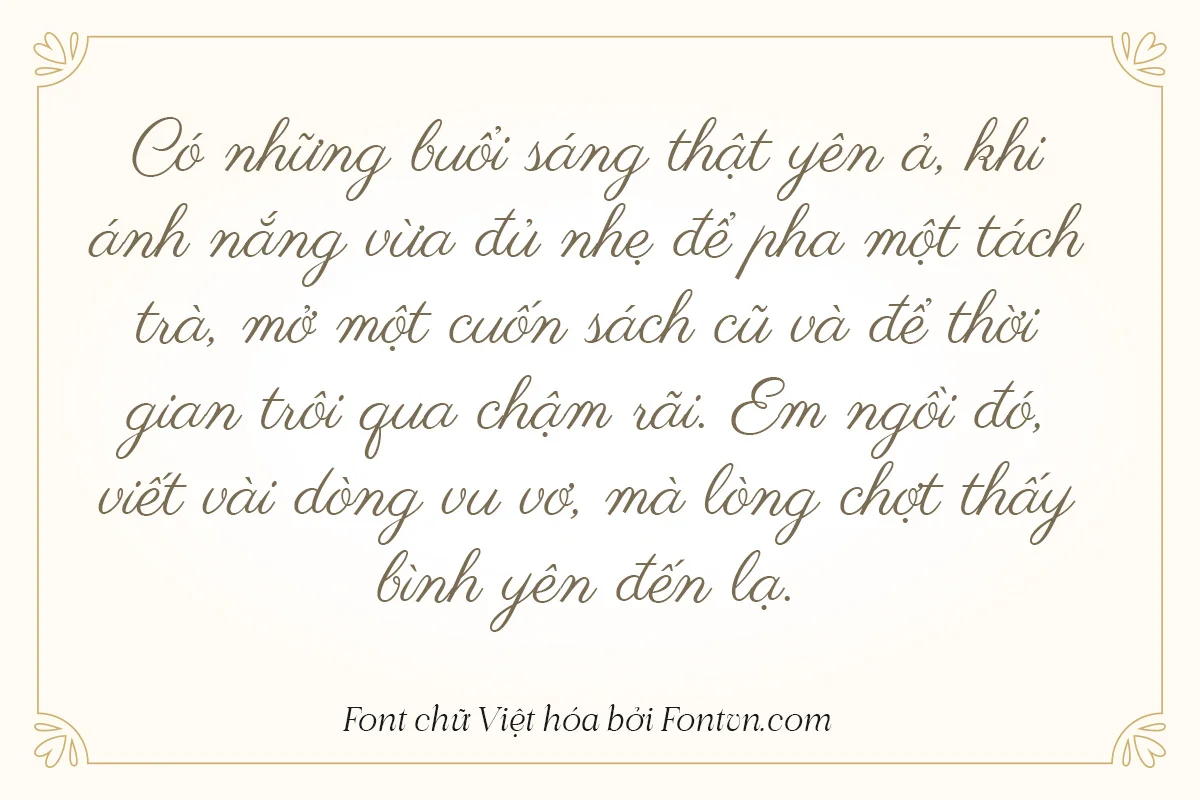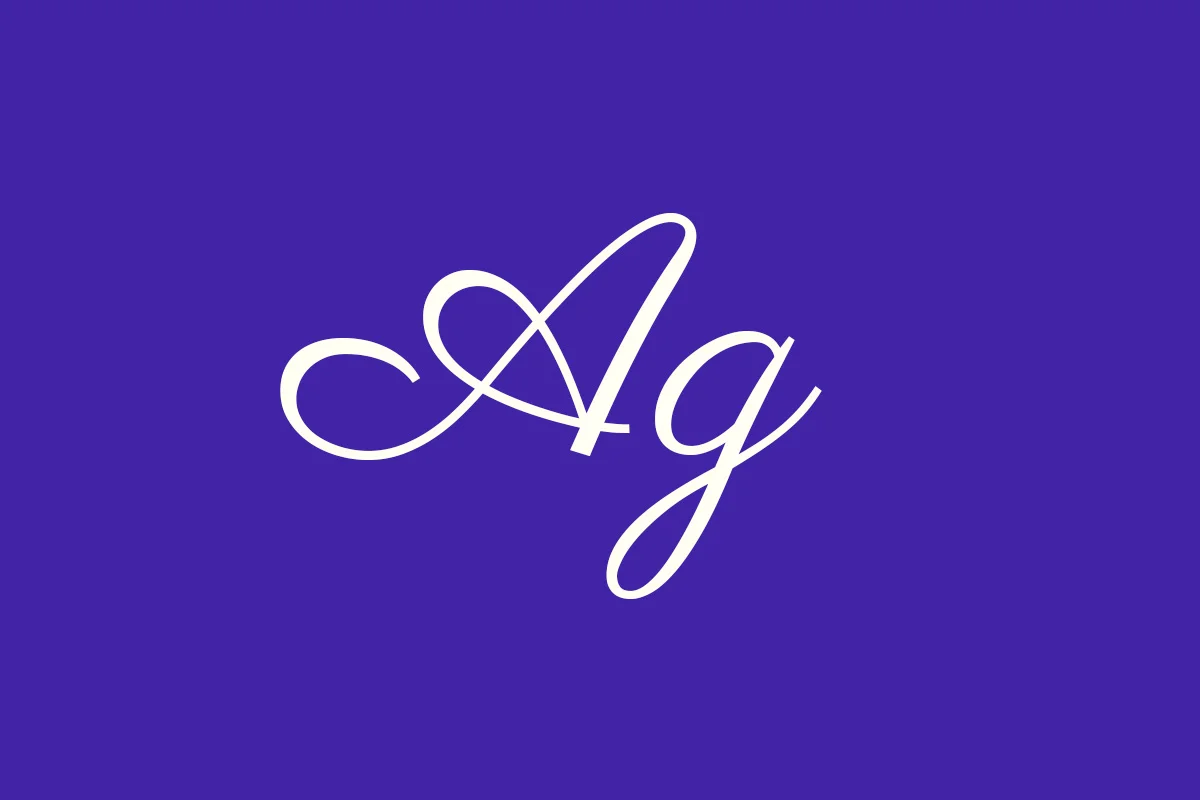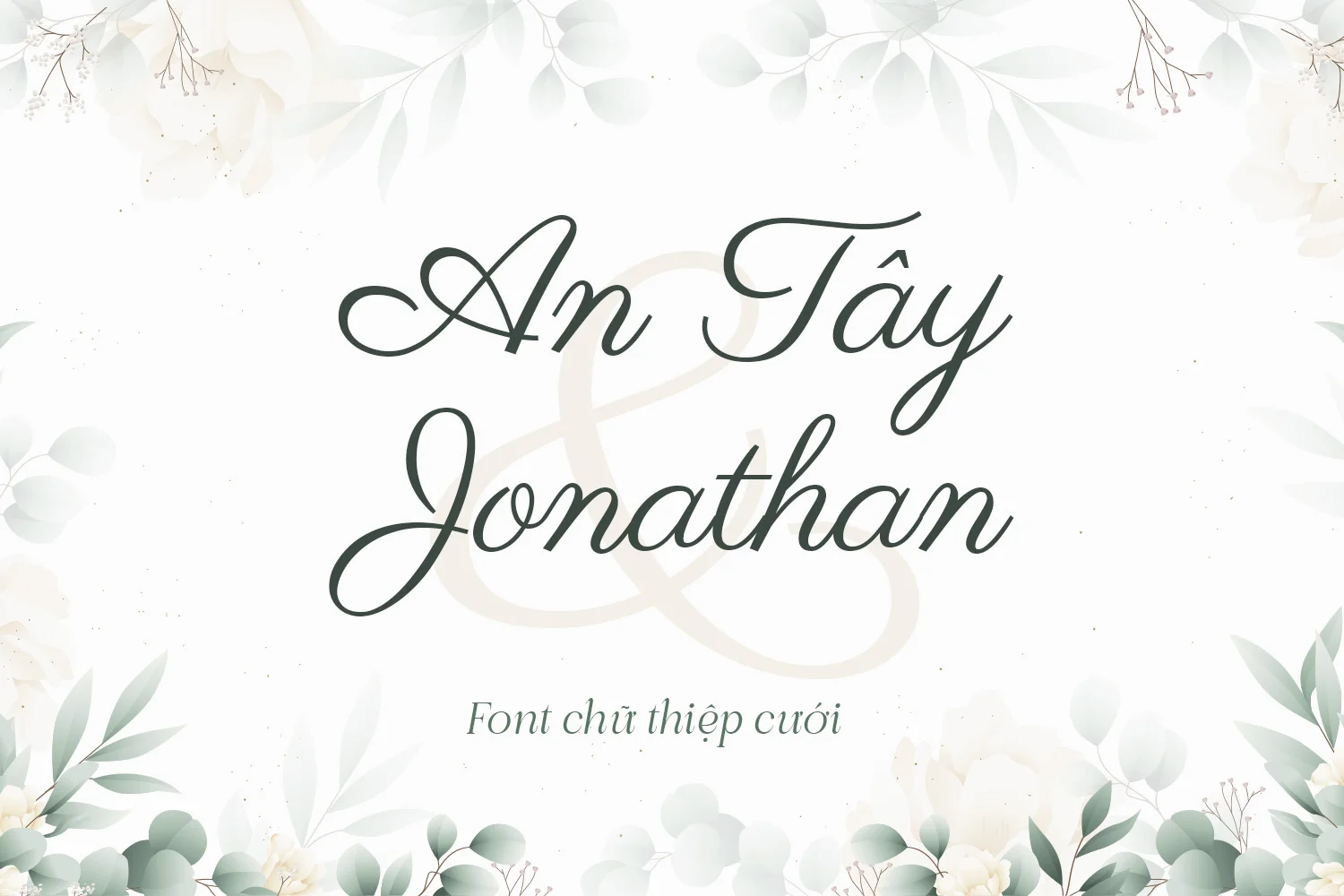
DVN Parisienne – Font Việt hóa phong cách viết tay đậm chất thanh lịch và sang trọng
DVN Parisienne Việt hóa là kiểu chữ script mang phong cách viết tay hiện đại, với các đường nét mảnh, mềm mại và đầy tinh tế. Font gợi cảm giác thanh lịch, tự do, và đầy phong thái — như một lời thì thầm nhẹ nhàng giữa nhịp sống bận rộn. Phiên bản Việt hóa giữ trọn nét duyên dáng của bản gốc, đồng thời tối ưu cho hệ chữ tiếng Việt với dấu sắc nét và bố cục hài hòa. Phù hợp cho các thiết kế thời trang, logo mỹ phẩm cao cấp, thương hiệu lifestyle, tiêu đề blog cá nhân hay những layout mang hơi hướng Pháp cổ. DVN Parisienne không chỉ là một kiểu chữ — mà còn là phong cách sống: nữ tính, thanh thoát và tự tin.